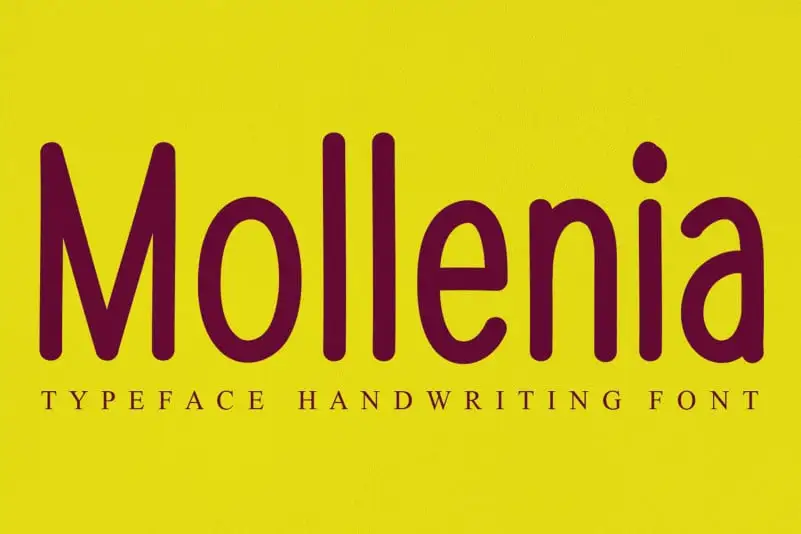
Mollenia Script Font – Download Grátis
Descubra uma nova experiência de escrita com Mollenia Script Font, um recurso criativo para designers digitais do andikastudio. Com seus traços fluidos e personalizados, essa fonte é perfeita para criar textos envolventes e emotivos. Seu design delicado e elegante permite que você personalize o texto de uma maneira única, tornando-o acentuadamente seu. Ideal para aplicações em websites, publicações digitais ou qualquer projeto gráfico onde um touch especial de texto seja desejável. Engane-se na atmosfera sofisticada e harmoniosa do Mollenia Script Font. Seja você quem escreverá com ele.